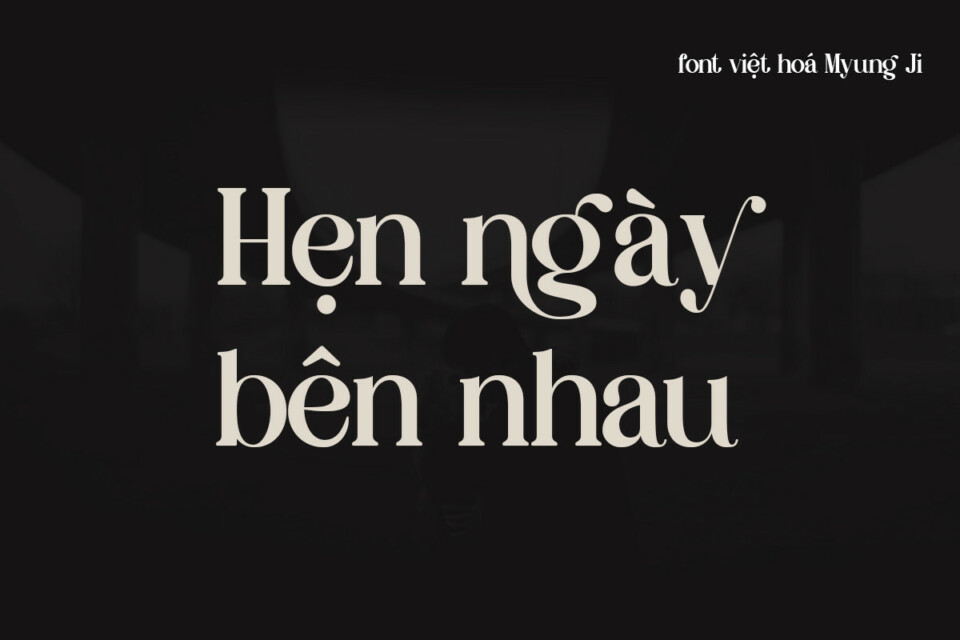
Font việt hoá MJ Glamour Coquette – Vẻ đẹp sang trọng và cổ điển cho thiết kế
Giới thiệu về Font việt hoá MJ Glamour Coquette
Trong thế giới đồ họa hiện đại, việc lựa chọn một bộ Font Chữ phù hợp đóng vai trò quan trọng trong việc truyền tải cảm xúc của tác phẩm. Font việt hoá MJ Glamour Coquette là sự kết hợp hoàn hảo giữa nét kiêu sa, cổ điển và sự tinh tế đương đại. Bộ font này được lấy cảm hứng từ phong cách thời trang cao cấp, mang đến những đường nét thanh mảnh nhưng không kém phần sắc sảo. Đối với các bạn học sinh và thầy cô giáo, đây là công cụ hỗ trợ đắc lực để tạo ra những bài thuyết trình ấn tượng hoặc các ấn phẩm văn hóa học đường độc đáo, giúp nội dung trở nên sinh động và chuyên nghiệp hơn.
Đặc điểm nổi bật của Font việt hoá MJ Glamour Coquette
Thiết kế thanh lịch và đa dạng ứng dụng
Font việt hoá MJ Glamour Coquette nổi bật với các ký tự được trau chuốt tỉ mỉ, giúp tối ưu hóa khả năng hiển thị trên cả màn hình kỹ thuật số và bản in. Điểm đặc biệt của phiên bản việt hóa này chính là sự tương thích hoàn toàn với bảng mã Unicode, giúp người dùng dễ dàng gõ tiếng Việt mà không lo lỗi font hay mất dấu. Với phong cách Coquette đầy nữ tính và quý phái, bộ chữ này rất phù hợp để thiết kế thiệp mời, bìa sách, hoặc các tiêu đề trang trí nghệ thuật. Sự mềm mại của các đường cong tạo nên một tổng thể hài hòa, giúp người xem cảm thấy dễ chịu và bị thu hút ngay từ cái nhìn đầu tiên.